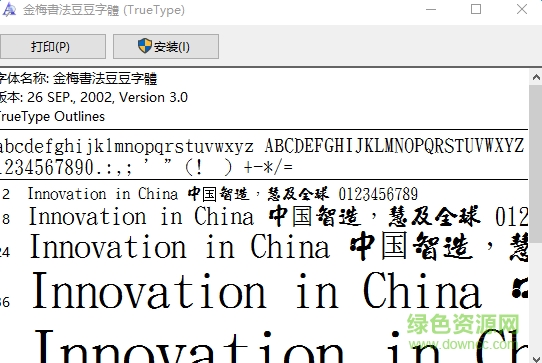
金梅書法豆豆字體是一款很有特色的電腦字體,該字體寫出來(lái)的字很好看,而且大氣美觀,適合用于藝術(shù)設(shè)計(jì)、書法寫作等,大家如果喜歡這款字體可以來(lái)綠色資源網(wǎng)下載。
金梅書法豆豆字體是一款很不錯(cuò)的書法字體,所以用在書法方面當(dāng)然是最合適的,也是最完美的,歡迎大家來(lái)綠色資源網(wǎng)下載。